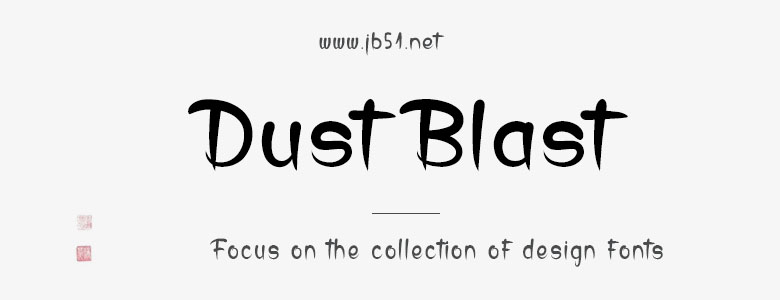
Dust & Blast英文手寫字體,字體筆觸略粗,字形圓潤(rùn),具有很好的視覺(jué)感,適合應(yīng)用于藝術(shù)設(shè)計(jì)、平面宣傳設(shè)計(jì)、網(wǎng)頁(yè)設(shè)計(jì),書(shū)法字帖等領(lǐng)域。有需要的朋友快來(lái)本站下載使用吧。